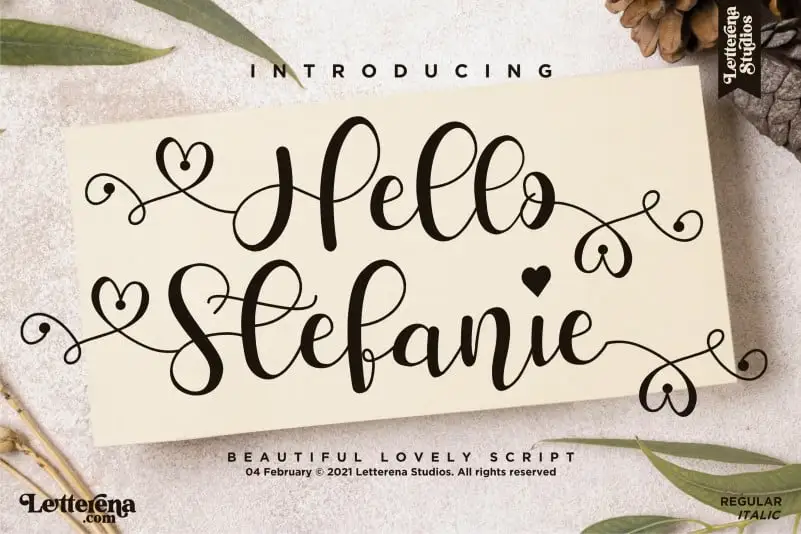
Hello Stefanie Calligraphy Font – Download Grátis
A fonte “Hello Stefanie Calligraphy Font” é uma elegante escolha para projetos diversos. De logo a etiquetas, do merchandising até os mais personais cartões de convite, ela traz um toque romântico e delicado ao seu design. Esta fonte de calligrafia script foi criada pela designer letterenastudios e é perfeita para qualquer projeto que valorize uma aparição agradável do tipo de letra. A sua utilização em desenhos de mobiliário, embalagens de produto e até mesmo na customização de mug ou cartões personalizados, evidencia a versatilidade desta fonte. O seu design curvilíneo permite que você crie designs únicos e memoráveis com um toque delicado e pessoal. Seja para criar uma identidade visual única, decorar suas obras ou simplesmente adicionar elegância aos seus designs digitais, “Hello Stefanie Calligraphy Font” é certamente a fonte perfeita. Que tal incorporá-la em seu próximo projeto?